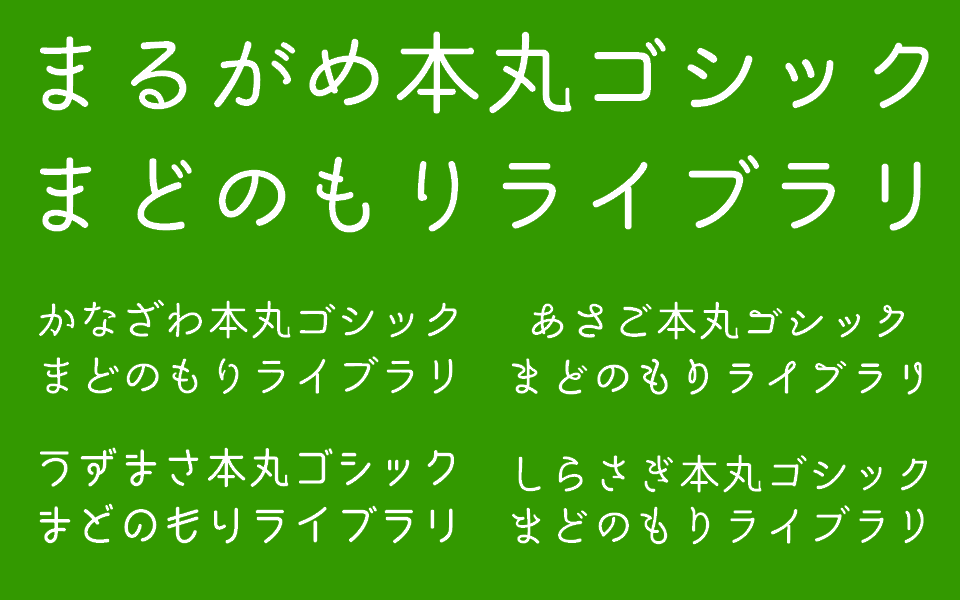
年賀状の書体を自分や相手の住所で使い分けたくなるフォント群「本丸ゴシック」
「本丸ゴシック」は、日本各地の城下町が醸し出す風情を文字化したフォント群。2016年12月現在では丸亀城と丸亀市の「まるがめ本丸ゴシック」、金沢城と金沢市の「かなざわ本丸ゴシック」、竹田城と朝来市の「あさご本丸ゴシック」、京都市太秦の「うずまさ本丸ゴシック」、白鷺城と姫路市の「しらさぎ本丸ゴシック」で構成される。
いずれもひらがな、カタカナ、英数字、記号のほか、1,006字の教育漢字を収録。明朝体の骨格がおおよそ共通しており、丸ゴシック体の肉付けによって城下町の表情を書き分けたデザインだ。ただし、無声チャンバラ映画の字幕文字を再現する「うずまさ本丸ゴシック」だけは骨格も毛色も異なる。
とくにオススメしたい使い方は年賀状などの挨拶状印刷。たとえば、香川県在住なら「まるがめ本丸ゴシック」、兵庫県在住なら「あさご本丸ゴシック」または「しらさぎ本丸ゴシック」といったように、年賀状用の書体として選んでみるのはどうだろうか。面倒でないなら宛先ごとに使い分けるのもよい。